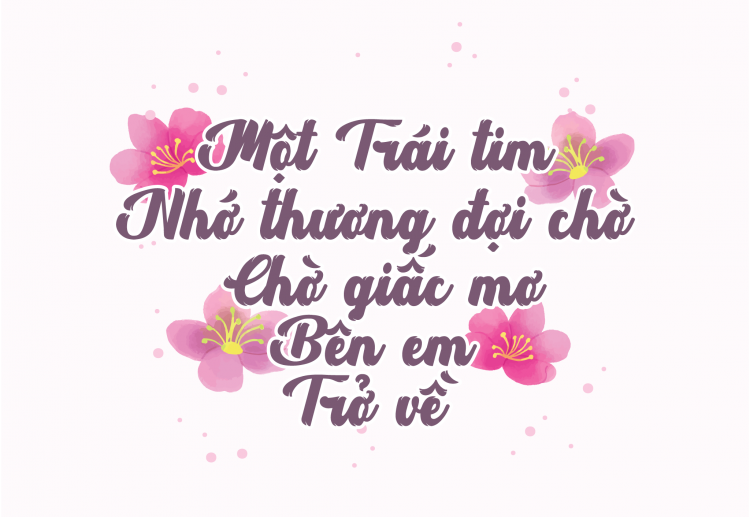
Font việt hóa LNTH Headbrush
Giới thiệu về Font việt hóa LNTH Headbrush
Trong thế giới đồ họa hiện đại, việc lựa chọn một bộ Font việt hóa LNTH Headbrush chất lượng là yếu tố then chốt để tạo nên sự khác biệt. Đây là một định dạng Font Miễn Phí mang phong cách cọ vẽ (brush) đầy mạnh mẽ, phóng khoáng và tràn đầy năng lượng. Với những đường nét thô ráp nhưng tinh tế, bộ font này mô phỏng chân thực những nhát cọ thủ công, mang lại cảm giác thủ công truyền thống đan xen với tinh thần hiện đại. Việc tìm kiếm một phông chữ hỗ trợ đầy đủ tiếng Việt không còn là khó khăn khi phiên bản LNTH Headbrush đã được tối ưu hóa hoàn hảo cho người dùng trong nước.
Ưu điểm nổi bật của bộ font này
Đặc điểm nổi bật nhất của Font việt hóa LNTH Headbrush chính là sự linh hoạt trong sử dụng. Các ký tự được thiết kế với độ đậm nhạt khác nhau, tạo nên hiệu ứng thị giác ấn tượng cho các tiêu đề quảng cáo, bìa sách hoặc logo thương hiệu. Với khả năng hỗ trợ tiếng Việt trọn vẹn, bạn có thể tự tin sáng tạo mà không lo lỗi font hay thiếu dấu. Đây là lựa chọn lý tưởng cho các bạn học sinh, sinh viên và giáo viên trong việc thiết kế slide bài giảng hoặc trang trí báo tường sinh động.
Cách ứng dụng Font việt hóa LNTH Headbrush hiệu quả
Để tận dụng tối đa vẻ đẹp của bộ font này, người dùng nên kết hợp với những tông màu tương phản hoặc đặt trên nền ảnh có chiều sâu. Font việt hóa LNTH Headbrush cực kỳ phù hợp cho các thiết kế mang tính cổ điển (vintage) hoặc phong cách đường phố (streetwear). Bạn có thể sử dụng nó làm điểm nhấn chính trong các thiết kế poster, banner sự kiện hoặc tiêu đề video YouTube để thu hút sự chú ý ngay từ cái nhìn đầu tiên.
Lưu ý khi sử dụng trong thiết kế chuyên nghiệp
Khi sử dụng bộ font này, bạn nên tránh dùng cho các đoạn văn bản dài vì đặc tính nét brush có thể gây mỏi mắt. Hãy chỉ tập trung vào các cụm từ ngắn gọn, súc tích để đạt hiệu quả thẩm mỹ cao nhất. Sự kết hợp giữa nét chữ nghệ thuật và bố cục thoáng đãng sẽ làm tôn lên giá trị nội dung bạn muốn truyền tải.
Kết luận về bộ Font việt hóa LNTH Headbrush